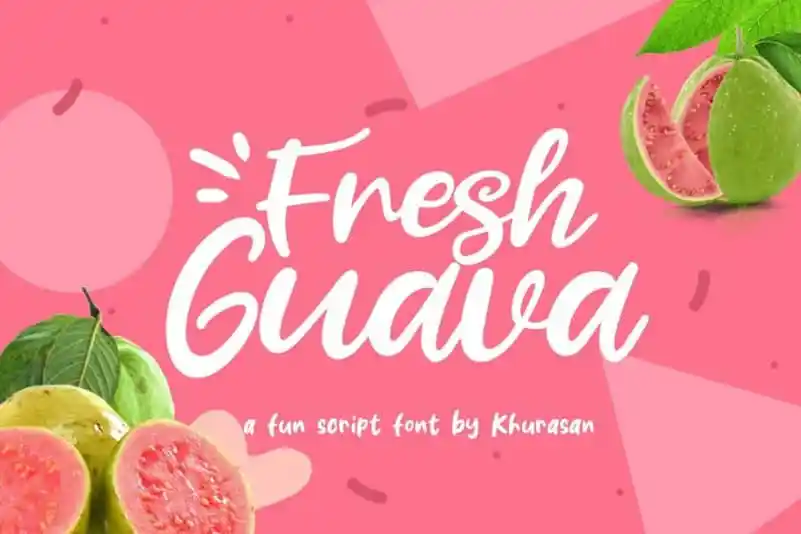
Fresh Guava Script Font – Fonte Grátis
Fresh Guava Script Font
A Fresh Guava Script Font é uma opção ideal para quem busca adicionar um toque único à sua designação. Originada a partir de inspirações na escrita por mãos, esta fonte contém todo tipo de letras do alfabeto e números, bem como sinais de pontuação. Ela foi criada pela equipe da Khurasan e oferece uma experiência gráfica vibrante e alegre. Perfeita para projetos que exigem um design divertido e dinâmico, esta fonte é particularmente versátil e multilíngue, suportando múltiplas línguas de maneira incrivelmente fluida. A Fresh Guava Script é uma opção ideal para diversos tipos de desenhos, desde logos e marcas a cartões de agradecimento e postais. A fonte também se ajusta perfeitamente à criação de qualquer tipo de projeto visual que você possa imaginar. Em um mundo onde cada design conta, esta fonte oferece uma maneira elegante e autêntica de expressar sua personalidade.